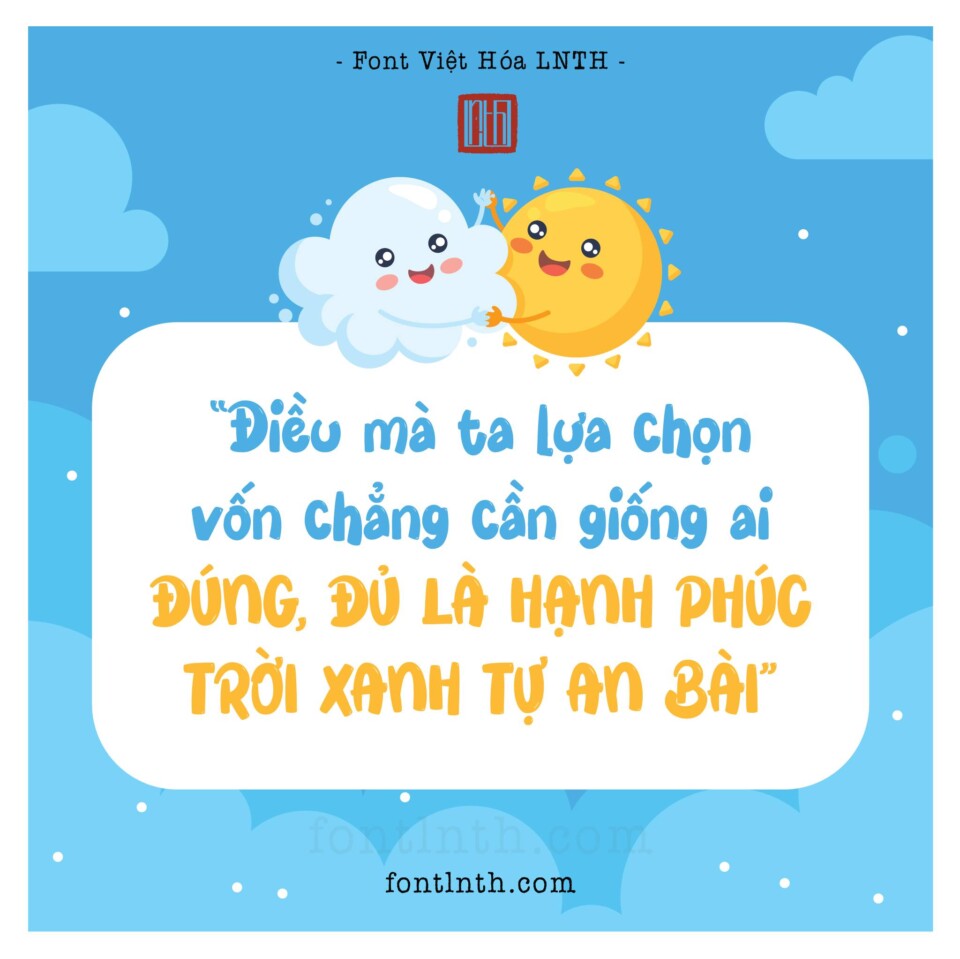
Giới thiệu về Font việt hóa LNTH Blue Cheries
Trong thế giới đồ họa hiện đại, việc lựa chọn Font Chữ phù hợp đóng vai trò quyết định đến tính thẩm mỹ của sản phẩm. Font việt hóa LNTH Blue Cheries là một bộ phông chữ mang phong cách Brush Script đầy nghệ thuật, được trau chuốt tỉ mỉ để phù hợp với ngôn ngữ tiếng Việt. Với những đường nét uyển chuyển, mềm mại nhưng không kém phần mạnh mẽ, bộ font này đã trở thành lựa chọn ưu tiên cho các bạn học sinh, sinh viên và giáo viên khi thiết kế bài giảng hoặc thiệp mừng. Phiên bản việt hóa giúp loại bỏ hoàn toàn lỗi hiển thị dấu, mang lại trải nghiệm sử dụng mượt mà nhất trên các phần mềm thiết kế phổ biến.
Đặc điểm nổi bật của bộ Font việt hóa LNTH Blue Cheries
Phong cách thiết kế thủ công độc đáo
Điểm thu hút nhất của Font việt hóa LNTH Blue Cheries chính là sự tự nhiên trong từng nét bút. Không giống như các phông chữ kỹ thuật số khô cứng, Blue Cheries tạo cảm giác như được viết tay trực tiếp bằng cọ vẽ. Điều này giúp các ấn phẩm thiết kế trở nên gần gũi, ấm áp và có hồn hơn. Các ký tự được liên kết với nhau một cách tinh tế, tạo nên dòng chảy thị giác lôi cuốn cho người xem ngay từ cái nhìn đầu tiên.
Tính ứng dụng linh hoạt trong giáo dục và đời sống
Bạn có thể sử dụng bộ font này cho nhiều mục đích khác nhau như làm tiêu đề báo tường, trang trí bìa sách, thiết kế poster sự kiện trường học hay tạo các trích dẫn truyền cảm hứng trên mạng xã hội. Sự linh hoạt của nó giúp người dùng dễ dàng tùy biến màu sắc và kích thước mà vẫn giữ được độ sắc nét tuyệt đối.